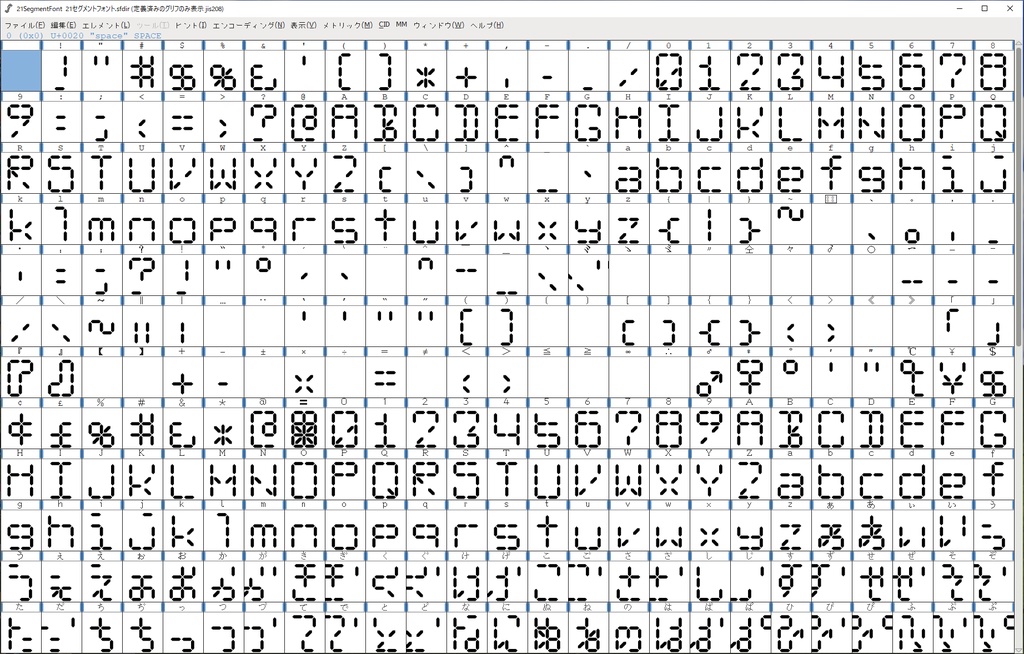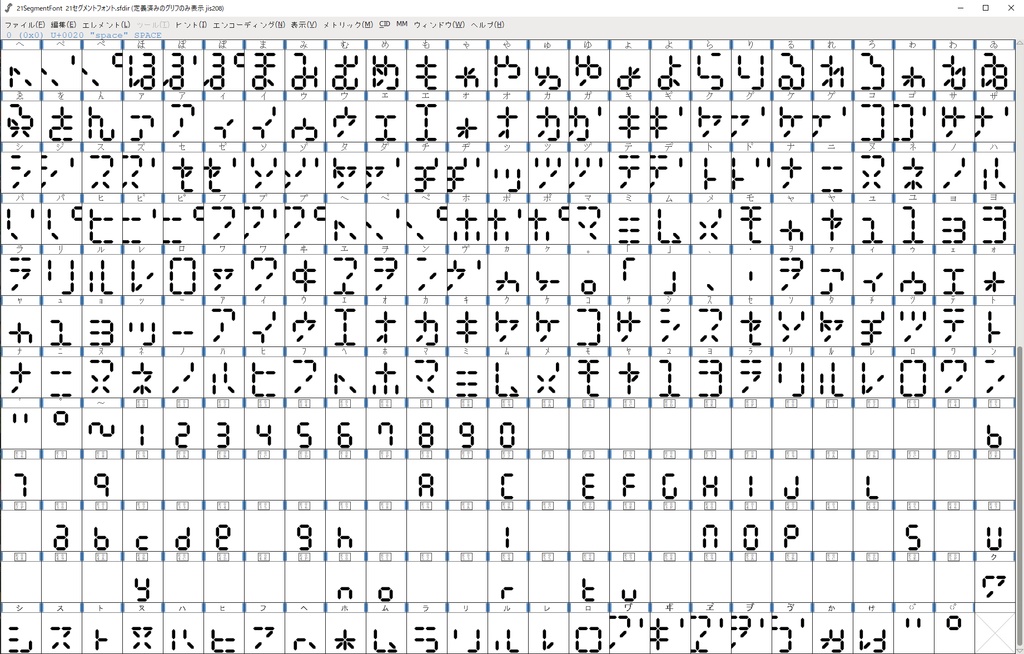
21セグメントフォント/21SegmentFont (2/15更新:ひらがな追加)
独自に考案した21本のセグメントを使ったカタカナと英数字のフォントです。 This is a katakana and alphanumeric font that uses 21 unique segments. 私用領域には7セグメントの英数字を収録しています。 The private area contains seven-segment alphanumeric characters. 商用利用可能(自己責任)、反社会的利用禁止でお願いします。 It may be used for commercial purposes (at your own risk), but anti-social use is prohibited. 収録文字:カタカナ、英数字、最低限の記号。 Characters included: Katakana, alphanumeric characters, and a minimum number of symbols. 2月15日更新:ひらがなを入れました。 Updated February 15th: Hiragana has been added.